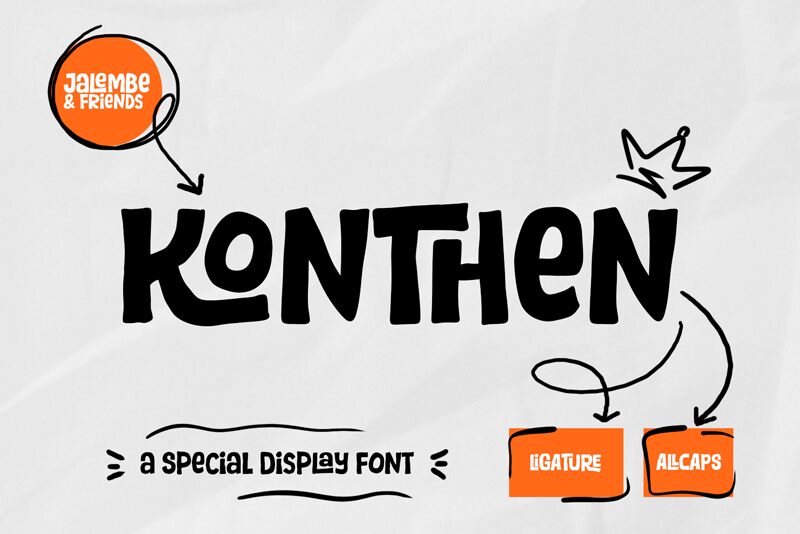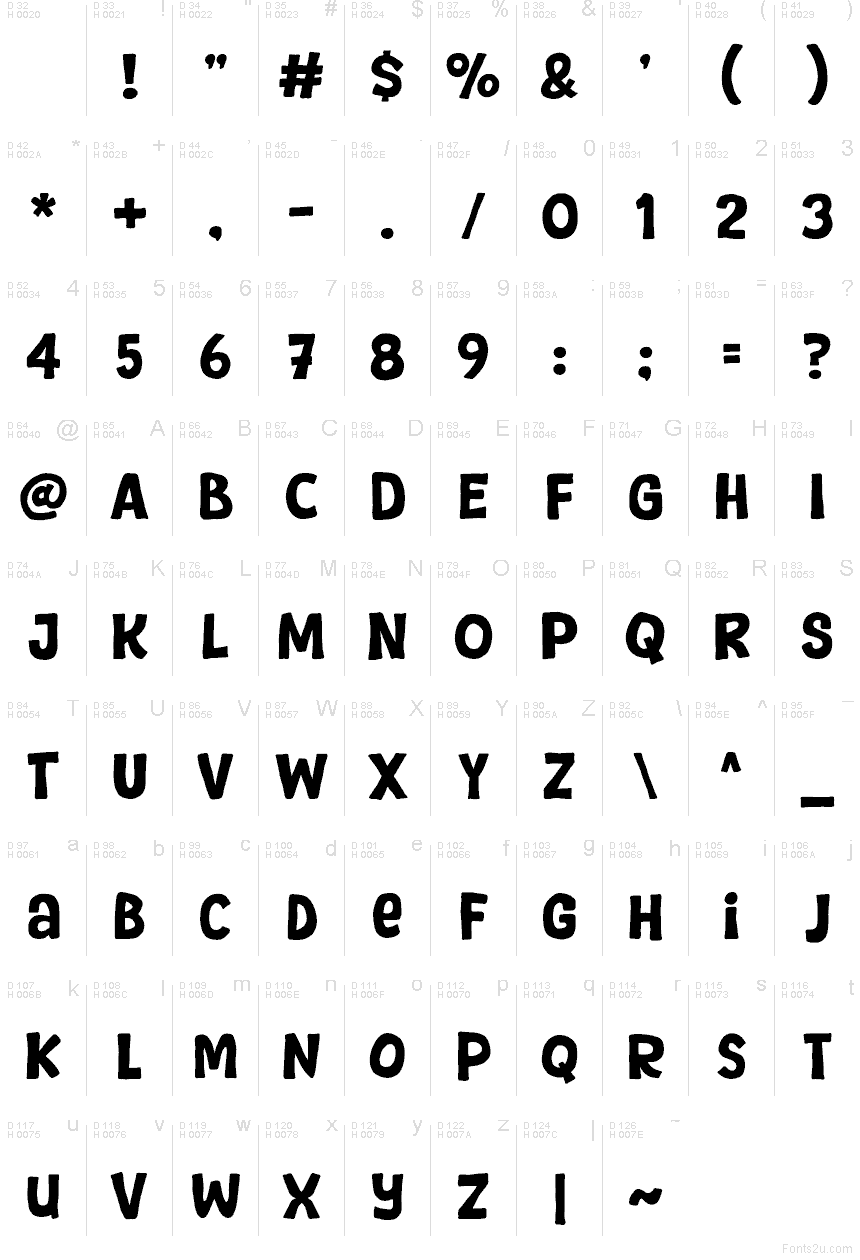
Konthen
Konthen от Khurasan & Jalembe - это бесплатный мультяшный дисплейный шрифт с мягкими, неровными кривыми, напоминающими ручную работу. Широкие округлые буквы со слегка «дрожащими» краями придают дизайну непринужденный, иллюстративный ритм, в отличие от выверенных геометрических шрифтов.
Konthen идеально подходит для логотипов, постеров, упаковки, детских проектов, комиксных заголовков и коротких графических элементов для соцсетей, где форма букв является главным акцентом. Этот бесплатный шрифт также отлично смотрится на стикерах и праздничной графике, ведь его живые контуры делают короткие надписи более дружелюбными и уютными.